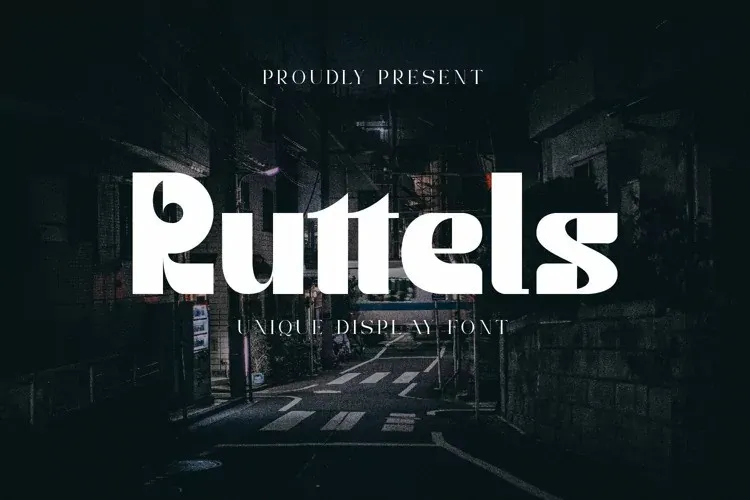
A Ruttels Font é uma excelente adição para designers que buscam uma mistura moderna entre as linhas futuristas e a simplicidade geométrica do Motter Ombra, inspirado pelo designer Othmar Motter. Com sua forma limpa e minimalista, a Ruttels se destaca como uma fonte de exibição perfeita para criar um impacto visual imediato em seus trabalhos visuais. Através da Ruttels Font, você pode trazer consigo temas futuristas sem comprometer sua legibilidade. Este é o tipo de font que ajuda a destacar seu trabalho, criando uma atmosfera envolvente e natural para qualquer projeto visual de design gráfico. Descubra por si mesmo como a Ruttels Font se transforma em um elemento chave no seu próximo design, mantendo-se sempre atual e moderno com seus temas inspirados nos principais desenhadores contemporâneos.